Шрифт без засечек кириллица – Кириллические шрифты — каталог бесплатных шрифтов, которые Вы можете скачать
Популярные и бесплатные шрифты без засечек
Хорошей альтернативой для стандартных шрифтов, используемых в веб-дизайне, являются пользовательские шрифты Sans Serif, или шрифты без засечек. Красивый и стильный пользовательский шрифт может сделать хороший дизайн намного лучше, потому что обычный и стандартный шрифт уже не является уникальным, в силу своего повсеместного использования. Я уверен, что уже не так интересен дизайн, в котором используется шрифт, который используется слишком часто, например, Arial или Georgia. Результат будет намного лучше, если вы замените такой стандартный шрифт на свой, пользовательский и уникальный.
QuickSand
Aller
Sansation
Colaborate
PT Sans
Titillium
Museo Sans
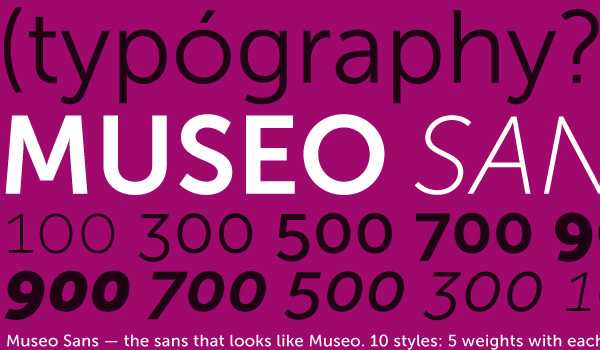
Cantarell
Bebas
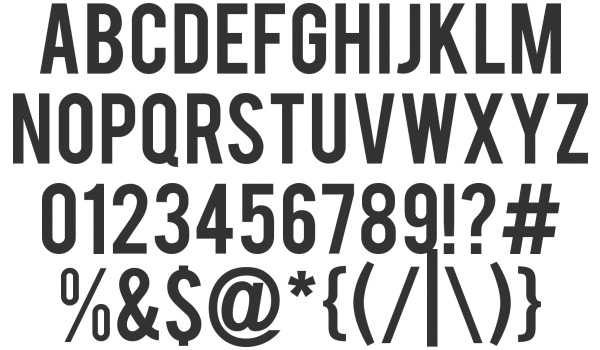
Droid Sans
Ubuntu
District Thin
Comfortaa
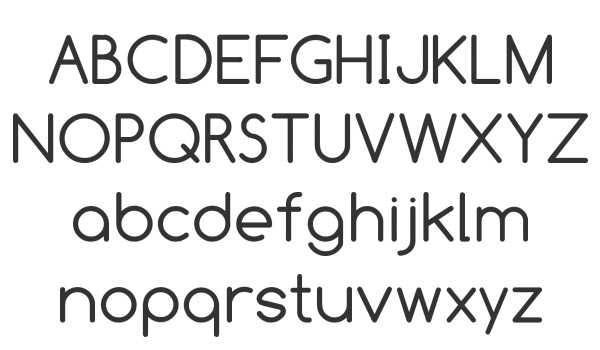
Yanone Kaffeesatz
League Gothic
Lane
Nobile
Fertigo Pro
Cicle
Aurulent Sans
Miso
CartoGothic
Bitstream Vera Sans
Josefin Sans
Hattori Hanzo
Raleway
Franchise
Greyscale Basic
Luxi Sans
Juice
11. Open Sans
Дизайнер: Стив Мэттэсон – дизайнер из штата Колорадо. Более 25 лет Мэттисон разрабатывает шрифты.
Типы: Light; Light Italic; Regular; Regular Italic; Semi-Bold; Semi-Bold Italic; Bold; Bold Italic; Extra-Bold; Extra-Bold Italic.
Open Sans – шрифт с простыми формами без засечек. Начертание букв плавное и широкое. Пакет оптимизирован для печатных, веб и мобильных интерфейсов.